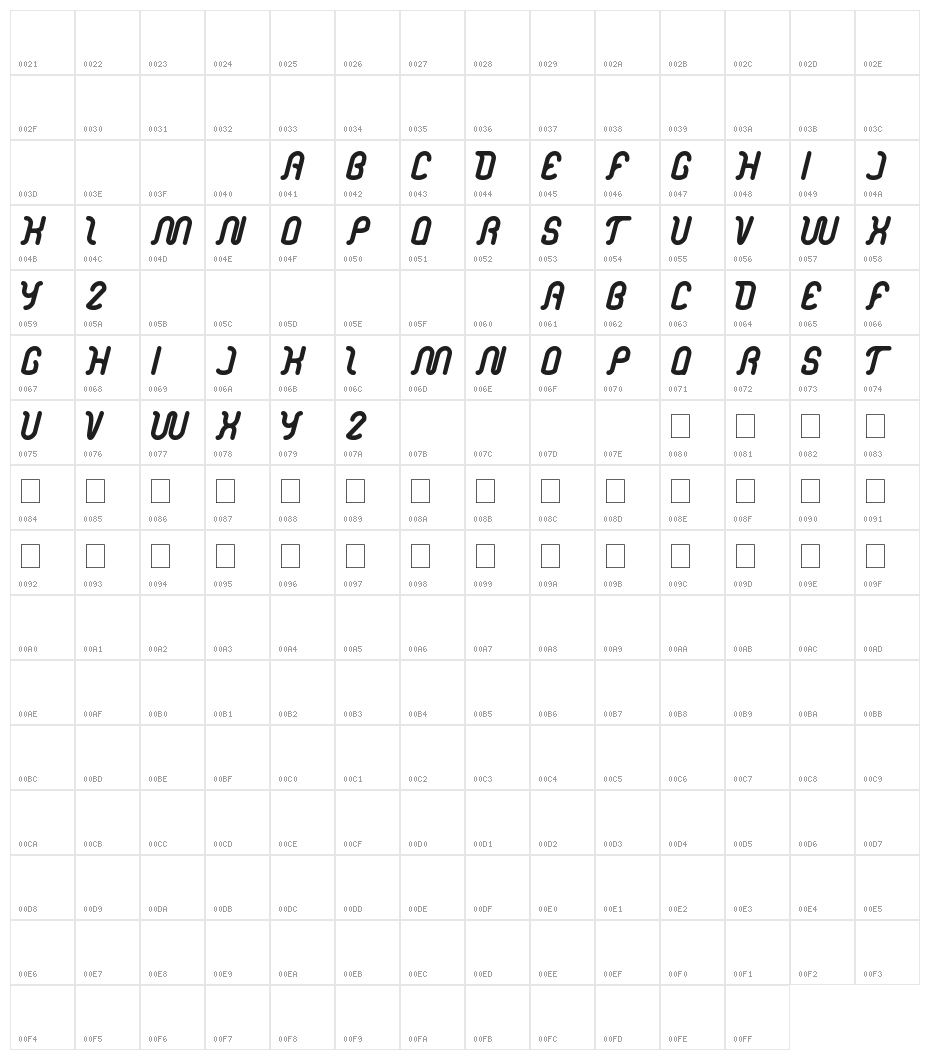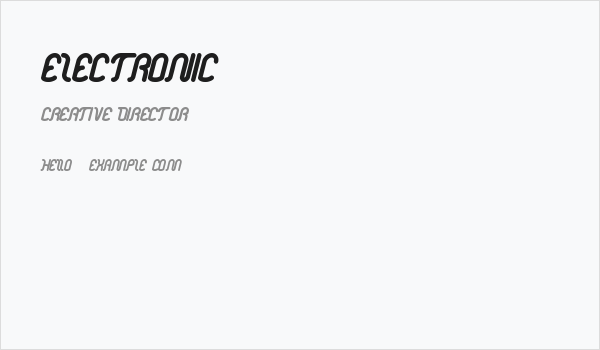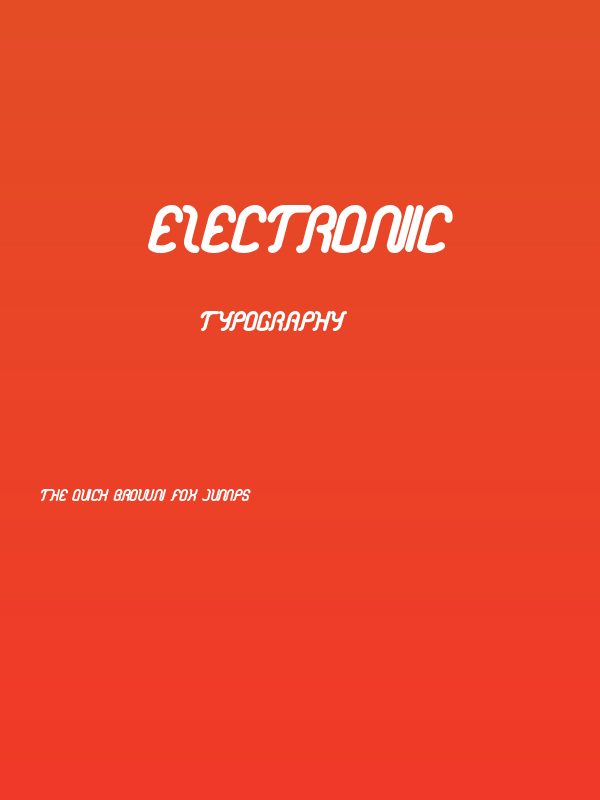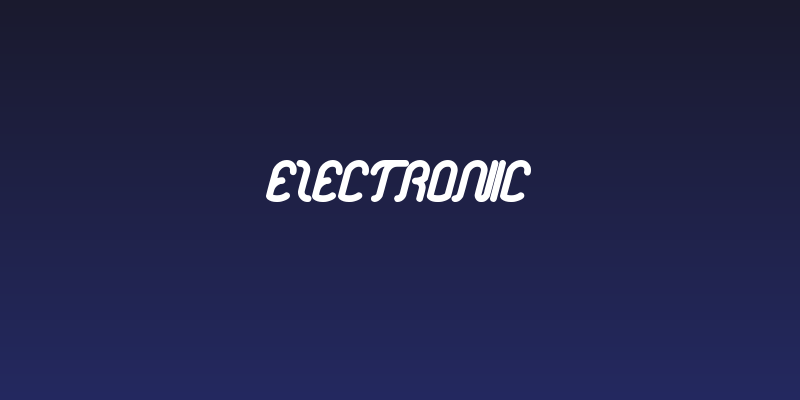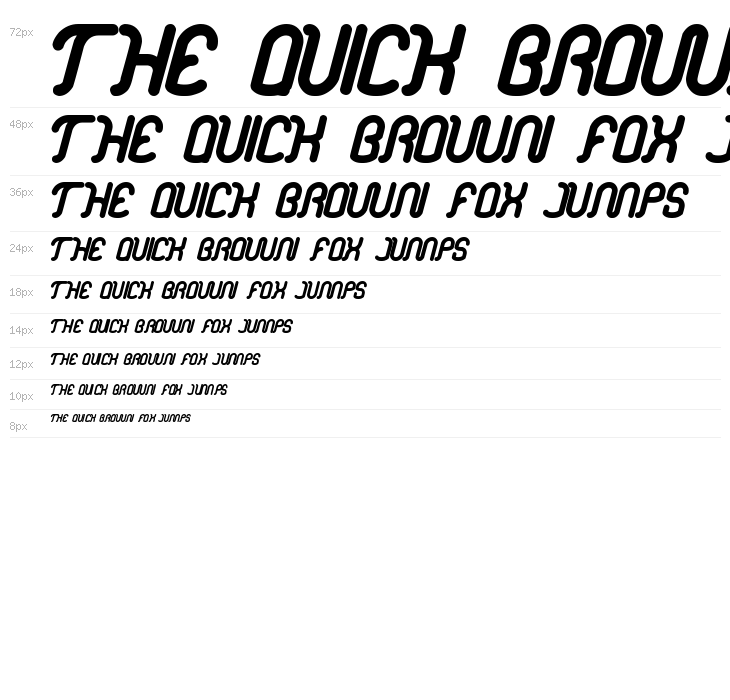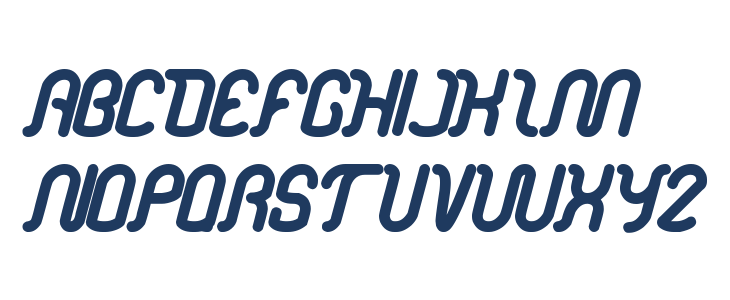
electronic Font
✎ Futuristic
| Vorgeschlagene Projekte | Ideal for branding, logos, headlines, and digital media projects that require a modern and energetic aesthetic. |